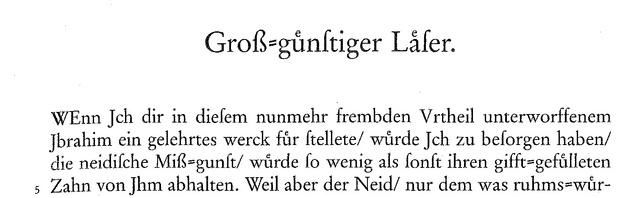
laut Verlag wurde Garamond verwendet.
Ich habe Garamond installiert. Im Original sieht das kleine s ähnlich wie ein „f“ nur ohne Querstrich aus: ſ.
Bei mir wird das kleine s („f“) jedoch mit einem kleinen Haken links dargestellt. Wieso?
Ich bin grad selbst erschrocken, was sich alles namens Garamond bei mir angesammelt hat … wie du siehst, gibt es nicht die Garamond. Sie unterscheiden sich alle in kleinen oder großen Details.
Adobe Garamond
Adobe GaramondPro
Adobe Garamond Alternate
Garamond Adobe
AGaramondExp
Adobe Garamond Titling Capitals
CgGaramond
ClassGarmnd
ClassicalGaramondBT
ElegaGarmnd
Garamond
Garamond 3
Garamond No2 DC D
G/Garamond No2 SC T
Garamond No2 T
Garamond No4 T
Garamond No5 D
Garamond Premier Pro
Garamond Premier Pro Caption
Garamond Premier Pro Display
Garamond Premier Pro Subhead
Garamond Stencil D
Garamond ITC
ITC Garamond
Garamond SC&OsF Stempel
Garamond Stempel Screen
Stempel Garamond
URW Garamond Stencil D
URW Garamond T
Mindestens zwei Bedingungen sollten erfüllt sein: 1.) Das kleine sieht so aus: ſ; 2.) Der Doppelstrich ist leicht gedreht.
Nur nebenbei: Das „ſ“ ist nicht „das kleine s“, sonder das Lang-s.
Der doppelte Bindestrich sieht – sofern nicht fälschlich mit dem Gleichheitszeichen verwechselt – immer so aus: ⸗ und heißt „Double oblique Hyphen“ (Unicode U+2E17), (HTML ⸗)
Die Monotype Garamond beispielweise hat das „ſ“ ohne Haken links.
Die Garamond Antiqua stellt das „latin small long s“ auch korrekt dar.
„Korrekt“ werden sie alle dargestellt, sofern im Zeichensatz vorhanden. Manche haben aber ein Hakerl links, manche nicht.
Es gibt Zeichensätze, die diese Zeichen beinhalten. Ob es sie immer digital gibt, wage ich allerdings zu bezweifeln. Die übereinander gestellten Buchstaben sind schlicht die alte Darstellungsform der Umlaute.
Wie macht es der Verlag? In der Beispiel-Datei scheint es gelungen.
Wie gesagt: Es gibt Zeichensätze, die diese Zeichen beinhalten. Ob es sie immer digital gibt, wage ich allerdings zu bezweifeln. Wahrscheinlich wurde das noch in Blei gesetzt.
Bei der Schrift im Bild scheint sich’s um die Stempel-Garamond zu handeln. Ich vermute, daß der Verlag eine angepaßte Fassung der Schrift benutzt. Du kannst aber auch mal bei Linotype nachfragen, ob sie die Schrift mit den benötigten Zeichen anbieten.
Ich bin mir ziemlich sicher, daß die Andron die Zeichen enthält, sie ist die beste Möglichkeit, die mir einfällt.
Kostenlos geht’s mit der Cardo und der Gentium, bei der der Bindestrich aber gerade ist:
Das kleine e liegt auf U+0364, der Bindestrich der Gentium auf U+A78A.
Das positionierst du gar nicht selbst, sondern das e über dem u ist 1 Zeichen, das ist einfach die Form des ü.
In der Gentium ist das kleine e ein Verbindungszeichen (combining character), das Du nach dem Grundzeichen (hier also dem u) eingeben mußt. In der Cardo ist das u mit darübergestelltem e ein vorgefertigtes Zeichen.
Welche Schriften unterstützen „⸗“ ?
"Unterstützt" wird das Zeichen von allen Schriften, da das Zeichen einen Unicode-Platz besitzt. Ob der Schriftgestalter das Zeichen auch gestaltet und in seine Schrift eingebaut hat, steht auf einem anderen Blatt. Da musst du in die Zeichenbelegung schauen, ob es auch wirklich vorhanden ist.
Wobei es unter dieser Unicode-Position eher in Systemschriften zu finden ist:
Mir ist es bislang öfter als OpenType-Variante begegnet – als Stylistic Set oder unter Historical Forms.
Was das Originalmuster im Ursprungsbeitrag angeht: ich denke auch, dass das eine Spezialanpassung ist. Die Satzweise scheint doch eigentlich Fraktursatz zu simulieren.
Richtig! Laut Setzer ist die Stempel Garamond der Firma Berthold die Grundschrift der Textausgabe.